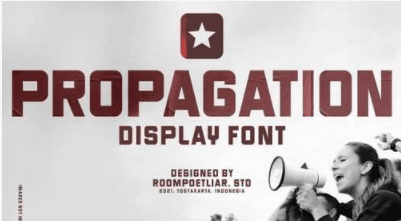
Propagation Font
Отображение шрифта распространения. Яркий, яркий шрифт, квадратный и четкий. Лучше всего подходит для дизайна плакатов, заголовков, типографских проектов (строительство, сопротивление, солидарность, движение, революция), логотипов киберспорта, текста на спортивной майке и т. Д.